BIC tükenmez kalem markası The Universal Typeface adlı proje ile kitle-kaynak (imece) yöntemini kullanarak evrensel bir font tasarımı projesine /deneyine başladı. Projenin çıkış noktası markanın Cristal adını verdiği kaleminin dünyada 100 milyondan fazla satılışını kutlaması aslında. Şimdi bunu dünyanın kolektif el yazısını oluşturabilecekleri proje ile daha da renkli hale getiriyorlar.
Siteye girdikten sonra size gösterilen harfleri farenizle çiziyorsunuz. Harfleri yazdığınızda, tarama mekanizması, sizin yazmış olduğunuz harfler ile diğer yazılanları karşılaştırarak ortak payda oluşturuyor.
Harflerinizi kimliğinizle Facebook’a bağlanarak ya da anonim olarak kaydetmeniz mümkün. Ayrıca projeye katılan diğer kişilerin bilgilerini de öğrenebiliyorsunuz. Mesela ülkelere, cinsiyete, sağ ve sol ele göre harflerin nasıl yapıldığına dair bilgileri sitenin ‘keşfet’ (explore) bölümünden görmeniz mümkün.
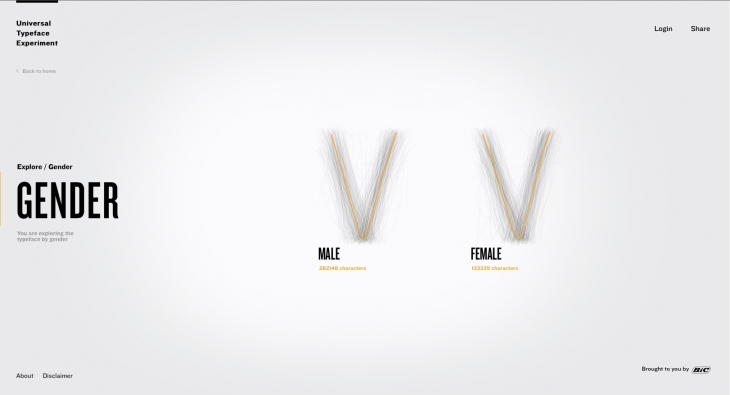
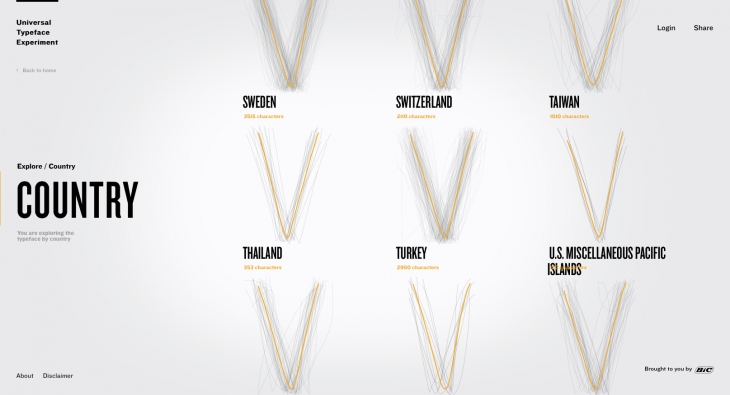
6 Haziran’da başlayan projenin sonuçları Ağustos ayında açıklanacak. Ağustos ayında evrensel bir font oluşturulmuş olacak.
Şu ana kadar 77 ülkeden 11.700’ün üzerinde kişinin katıldığı projeye dahil olabilirsiniz.